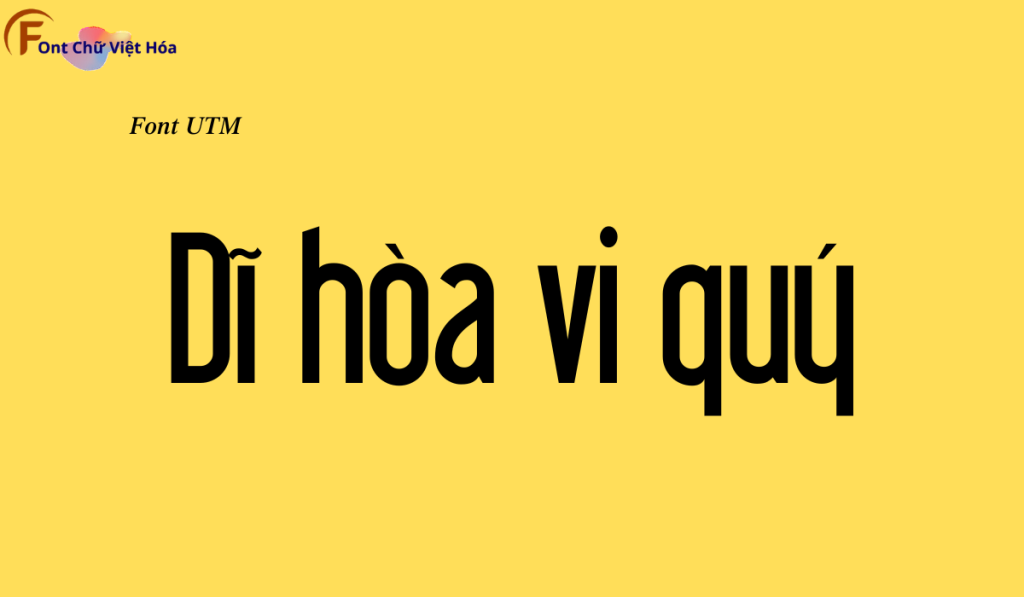
Font UTM Libel Kt Việt Hóa
Tác giả: UTM Libel Kt
Bộ Font: UTM
Phân loại: Cá tính, Độc đáo
Kiểu chữ: Chữ có chân
Font UTM Libel Kt Việt Hóa là một font chữ không chân độc đáo, thuộc bộ font UTM. Được thiết kế với mục tiêu mang lại sự sáng tạo và phá cách, font này lý tưởng cho các dự án thiết kế như logo, poster, và bao bì sản phẩm. Với các nét chữ sắc nét và độ dày đều đặn, Font UTM Libel Kt Việt Hóa không chỉ dễ đọc mà còn tạo cảm giác hiện đại và độc đáo. Việc Việt hóa font giúp người dùng dễ dàng tích hợp vào các thiết kế tiếng Việt, mang lại sự tiện lợi và nâng cao tính thẩm mỹ.